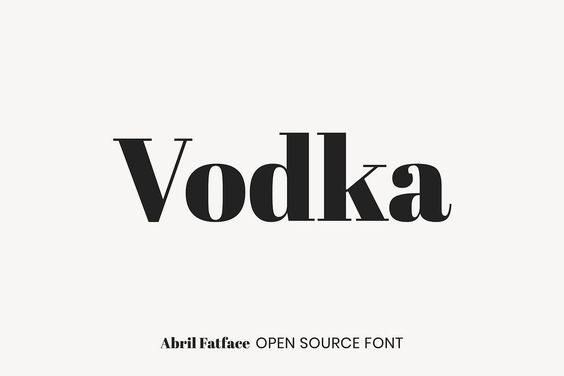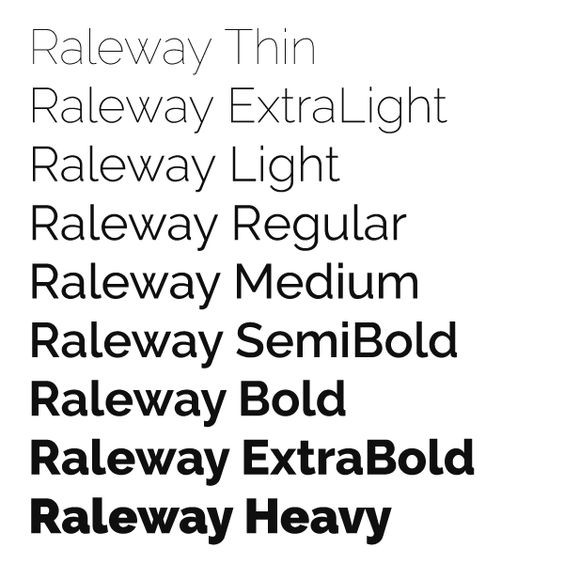
Las 15 mejores tipografías de Google Fonts
Google Fonts es una fuente de inspiración si quieres encontrar nuevas tipografías para tus diseños.
Este catálogo cuenta con cientos de fuentes gratuitas que te ayudarán a dar a tus trabajos ese toque único que estabas buscando. A continuación, te hablamos de las 15 mejores tipografías de Google Fonts.
¿Qué es Google Fonts y para qué sirve?
Google Fonts es uno de los recursos de Internet de mayor utilidad que existen actualmente en relación a la tipografía. Se trata de un directorio que tiene nada menos que más de 900 familias de tipos de letra, que puedes utilizar con absoluta libertad y completamente gratis, para todo lo que necesites y que tenga relación con el mundo digital y online. Esto se debe a que cuenta con licencia de uso open source, que quiere decir de código abierto.
Por tanto, puedes utilizar cualquiera de las tipografías incluidas en Google Fonts para todo tipo de proyectos. Desde los relacionados, por ejemplo, con una página web o con una aplicación de software hasta los proyectos relacionados con el diseño y creación de cualquier cartel. E incluso en la elaboración de documentos, y de diapositivas y presentaciones que realices con la ayuda de tu ordenador y programas de ofimática. Esto no quiere decir que las tipografías de Google Font sean de baja calidad. Más bien al contrario. Son familias de tipo de letra de una calidad más que notable, como comprobarás solo con echarles un vistazo.
El directorio de Google Fonts, al ser bastante extenso, incorpora un buscador para facilitar la localización de la tipografía que necesites. Te resultará muy útil si conoces su nombre, en todo o en parte. También puedes elegirlo para localizar una tipografía en función de las características que necesitas que tenga. Para ello, este buscador dispone de todo tipo de opciones, con las que filtrar los resultados y dar con el tipo de letra que necesites en cada caso.
Aunque no lo creas, las familias de fuentes de Google Fonts son bastante populares. Su uso está bastante extendido, y su presencia en todo tipo de ámbitos digitales no se limita a webs particulares y documentos y presentaciones personales y de empresa. Además, están integradas en proyectos y plataformas digitales de envergadura. Por ejemplo, en Canva, una plataforma dedicada al diseño. De esta manera, se reduce el número de quebraderos de cabeza al desarrollar cualquier proyecto digital que incorpore textos.
Mejores tipografías para tus diseños
Ahora que ya conoces qué es Google Fonts, te dejamos cuáles son las 15 mejores tipografías del momento.
Lato
Lato se caracteriza por su apariencia limpia y versátil, lo que la convierte en una elección popular para diversos proyectos de diseño. No tiene remates en los extremos, así que resulta elegante y contemporánea, y presenta una excelente legibilidad en diferentes contextos gracias a su proporción equilibrada. Además, ofrece una amplia gama de pesos y estilos, desde Thin (delgado) hasta Black (negro).
Playfair Display
Playfair Display es una elegante tipografía serif de Google Fonts. Con trazos delgados y serifs bien definidos, combina perfectamente lo clásico y lo moderno. Ideal para títulos y elementos destacados, su estilo sofisticado y legible añade un toque de refinamiento a cualquier diseño.
Cormorant
Cormorant es una tipografía serif elegante y refinada de Google Fonts. Sus trazos suaves y serifs delicados le otorgan un aspecto clásico y sofisticado. Con una amplia variedad de estilos y pesos, es perfecta para diseños elegantes y de alta calidad que buscan transmitir un aire de distinción y belleza.
Ubuntu
Ubuntu es una tipografía sans-serif moderna y legible. Con líneas limpias y proporciones equilibradas, es ideal para interfaces digitales y contenido en pantalla. Su diseño amigable y legible la hace adecuada para una amplia gama de aplicaciones, desde páginas web hasta presentaciones y documentos.
Alegreya Sans
Alegreya Sans es una tipografía sans-serif elegante y versátil. Con su aspecto moderno y legible, es ideal para textos largos y cuerpos de texto. Con una amplia variedad de pesos y estilos, ofrece opciones para transmitir distintas emociones y estilos visuales en diseños contemporáneos.
Cookie
Cookie es una tipografía manuscrita y encantadora de Google Fonts. Con letras redondeadas y una apariencia informal, evoca una sensación de calidez y amabilidad. Perfecta para proyectos creativos, invitaciones o elementos decorativos, Cookie añade un toque personalizado y acogedor a cualquier diseño con su estilo de escritura a mano, basado en el lettering realizado con pinzel.